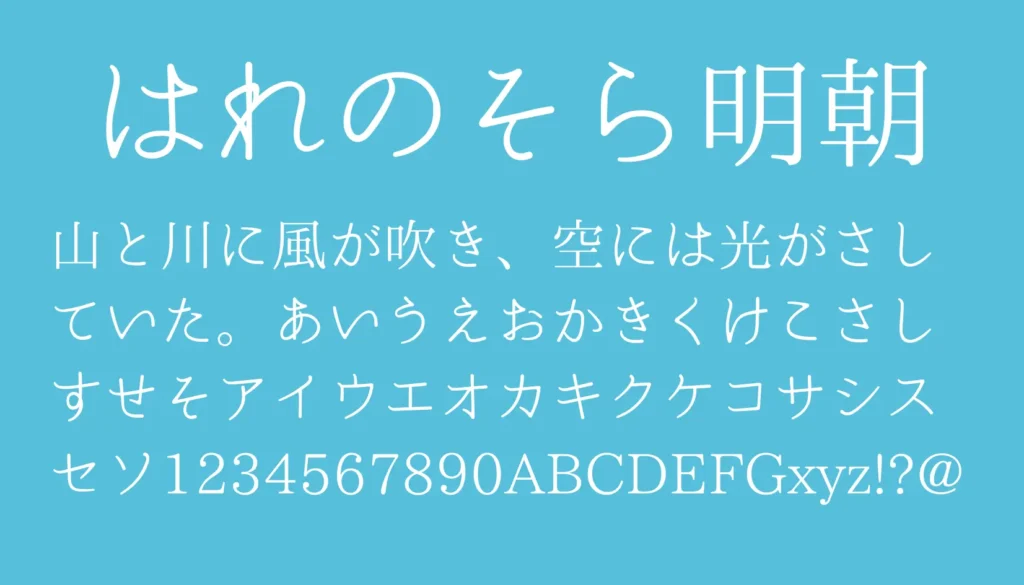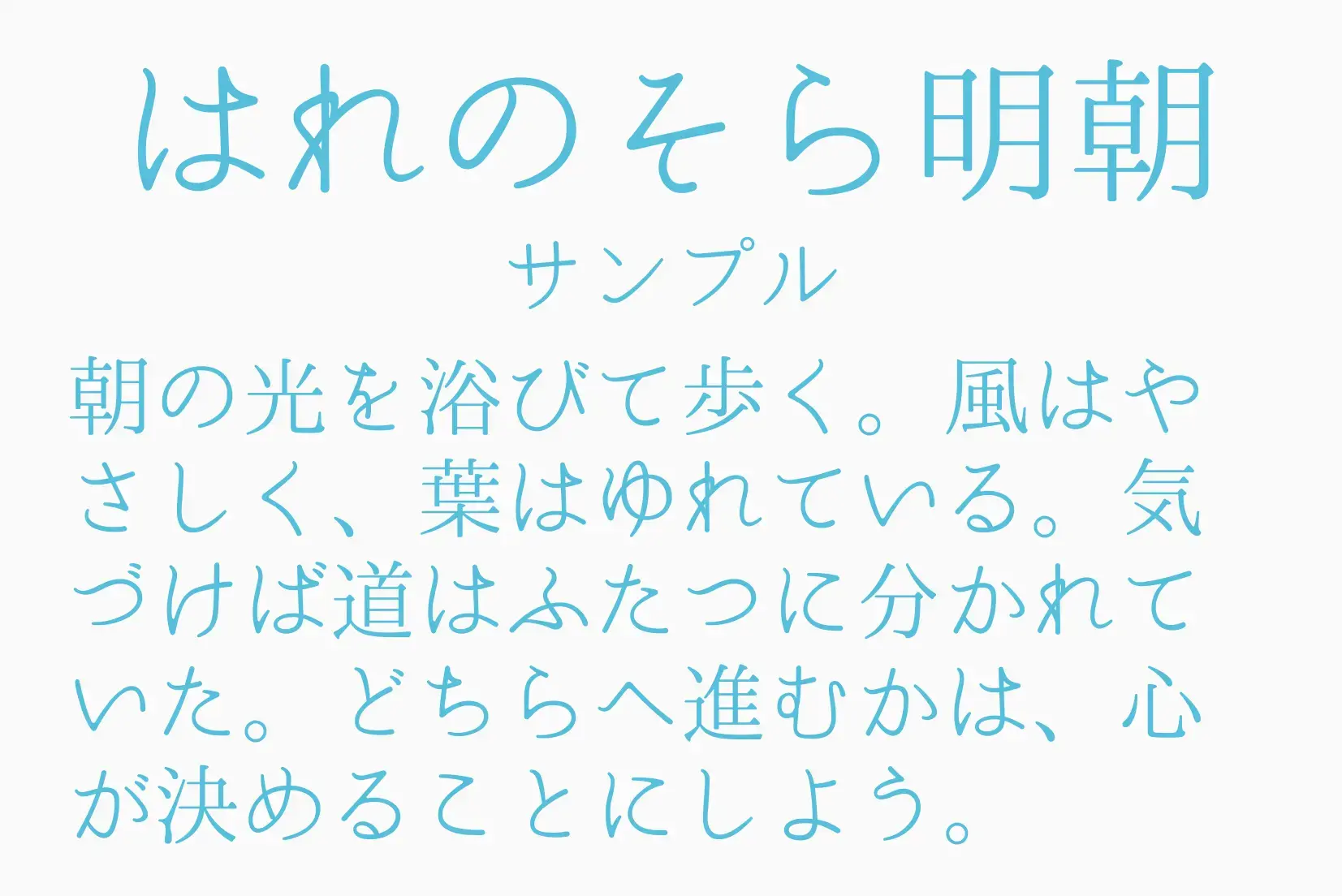
角丸処理と繊細な線のコントラストが特徴の明朝体フォントです。オールド系明朝の要素を取り入れつつ、すっきりとした現代的な印象も持ち合わせています。かな文字には筆の流れを感じるやわらかさがあり、全体として上品で女性的な雰囲気を演出。高級感や落ち着きを求めるデザインと相性がよく、Web・印刷どちらでも使いやすいバランス型の明朝体です。
はれのそら明朝